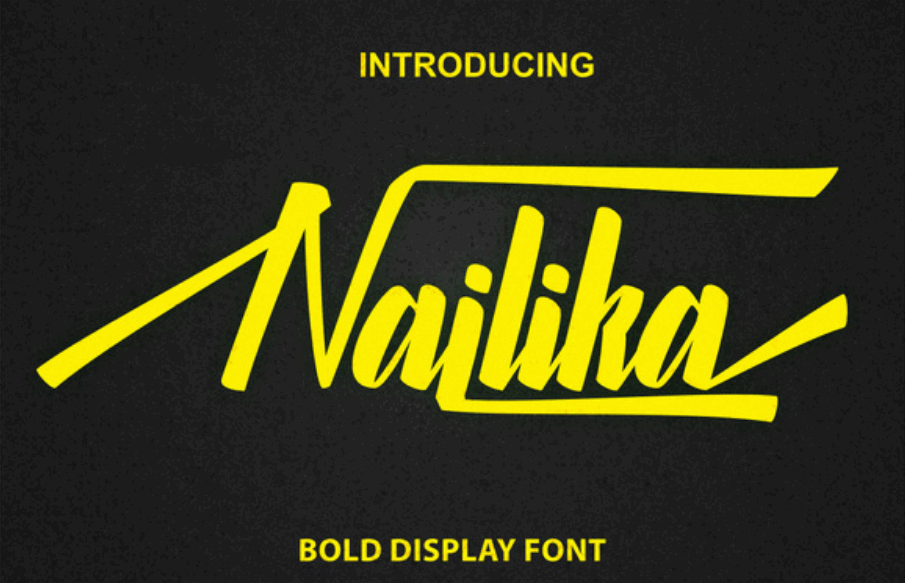
Agradecemos pela leitura. Estamos certos de que você irá apreciar a Nailika Script Font! Esta é uma fonte brushfont bold e linda, projetada para ajudar você a terminar seus projetos de design. O tipo opentype também está disponível na Nailika, oferecendo 2-6 alternativas de caracteres para cada letra única. Isso dá aos designers liberdade para explorarem suas impressões criativas através da Nailika. Esta fonte é perfeita tanto para designers gráficos quanto para aqueles que buscam algo diferente e interessante no seu trabalho. Não perca esta oportunidade de fazer as suas criações ainda mais incríveis!